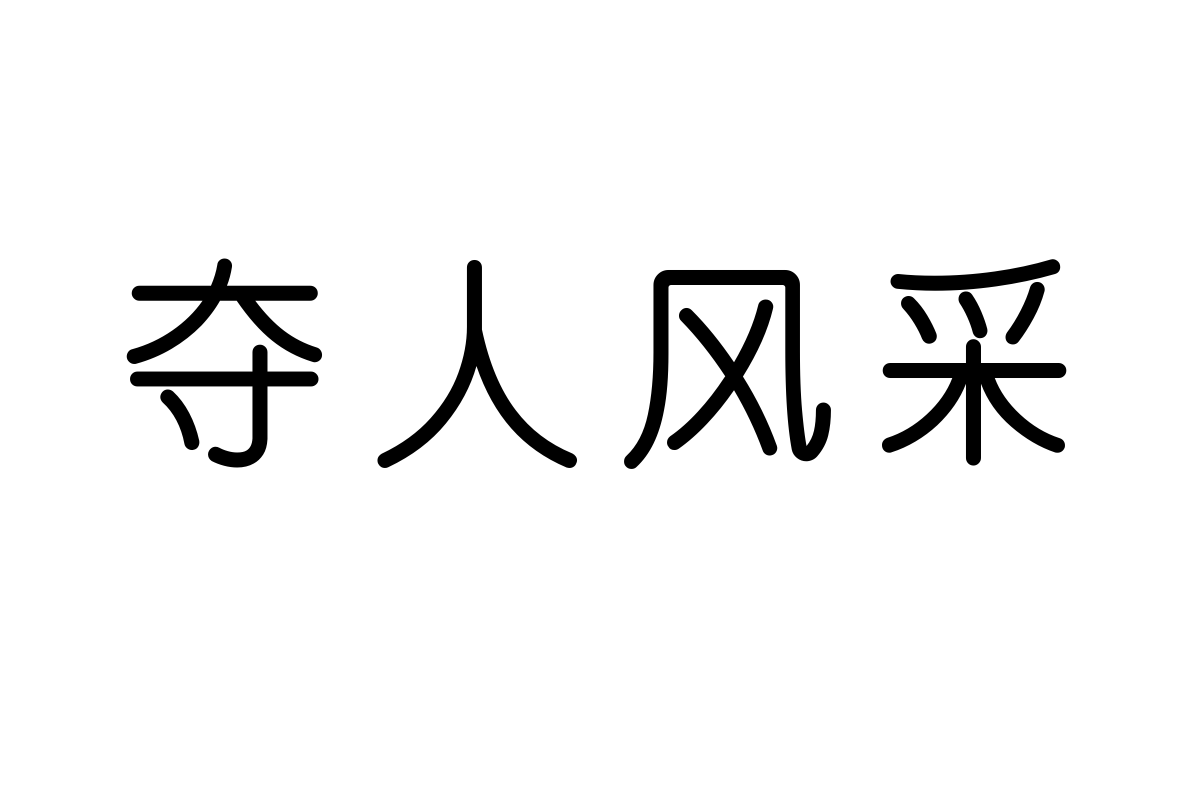
文道和圆体是一款具有独特风格的中文字体,它的设计灵感来源于中国传统书法和绘画艺术。这款字体的特点是笔画流畅、结构严谨,给人一种古朴典雅的感觉。
文道和圆体采用了圆润的字形结构,使得整体看起来更加和谐统一。它的笔画粗细适中,既有力度又不失柔美,给人一种优雅而庄重的感觉。同时,该字体还注重细节的处理,如笔画的起笔、转折等都经过精心雕琢,使得整个字形更加精致。
在风格上,文道和圆体融合了现代审美与传统元素,既保留了传统书法的韵味,又融入了现代设计的简洁线条。这使得它在各种场合都能展现其独特的魅力,无论是用于书籍、杂志还是广告宣传,都能给人留下深刻的印象。
总的来说,文道和圆体是一款非常出色的中文字体,它以其独特的风格和优美的字形结构,赢得了广大设计师和用户的喜爱。